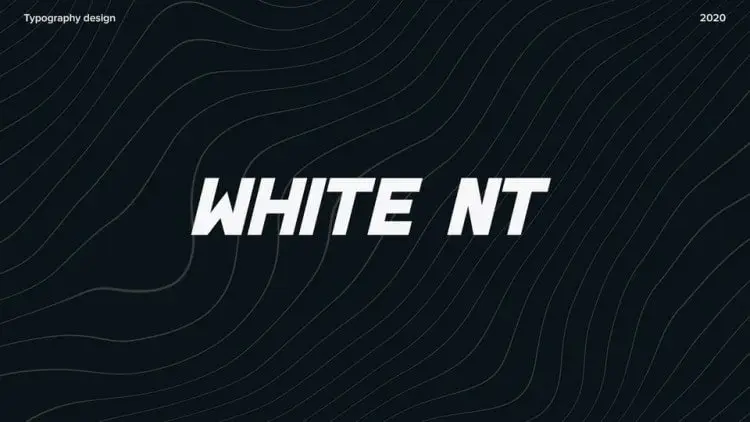
A White NT Display Font é uma coleção compacta e poderosa pronta para lidar facilmente com headlines e texto maior. Artyom Levanov criou esta tipografia para display, um tipo robusto e dinâmico que combina força visual e leitura fácil. Perfeito tanto para aplicação em esportes, anúncios automotivos, logotipos quanto para design de headlines. Seja para eventos esportivos ou criações visuais com texturas impactantes, a White NT Display Font atua como um aliado indispensável no seu arsenal criativo.